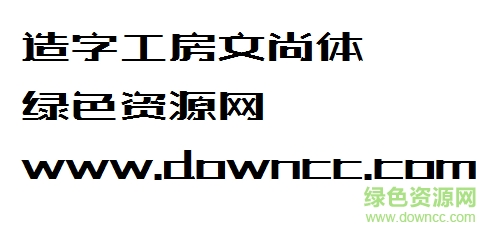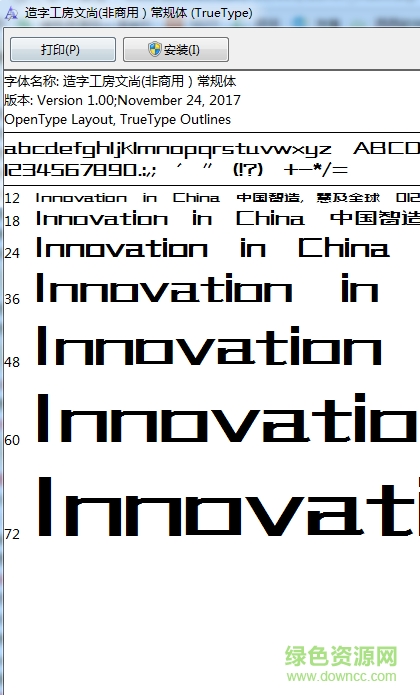
造字工房文尚體是一款文雅時(shí)尚的中英文字體軟件,字體一筆一畫(huà)非常穩(wěn)重,不雜亂,整體風(fēng)格十分端正,喜歡就到綠色資源網(wǎng)下載更多好看的造字工房字體吧!
造字工房文尚體字體造型規(guī)整,富于力度,給人以簡(jiǎn)潔爽朗的現(xiàn)代感,有較強(qiáng)的視覺(jué)沖擊力,這種個(gè)性的字體,適合于機(jī)械科技等主題。